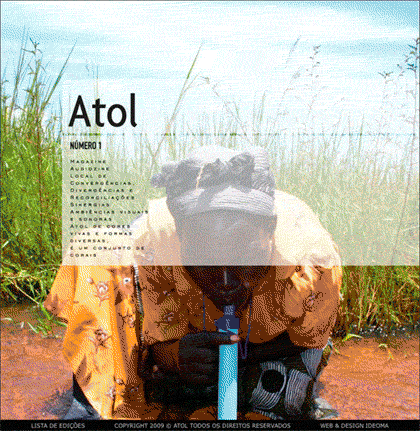
My name is Tiago Cartageno and I´m the Creative Director of Atol (www.atolmag.com). This is an online magazine from Portugal. We have just launched the number 1. I thought it would be great to show it to all the people we can inside the design world, hopping perhaps to find some exposure and divulge our work.
Réalisé au Portugal, mise en page élitiste, où l’illisible rend encore plus lisible l’intention artistique. La typographie joue ici à plein les effets musicaux dont parlait Massimo Vignelli dans le film l’Helvetica de Gary Hustwitt. Les espaces, les espaces… et quelques signes pour donner du sens.